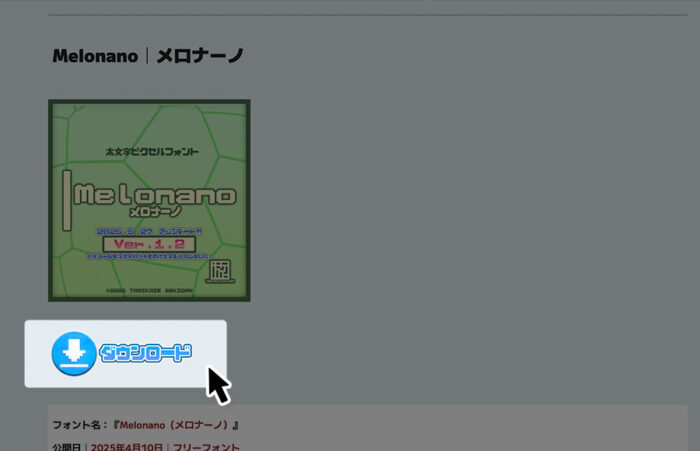
Melonano(メロナーノ)フォントは、コミカルで可愛らしい極太なピクセルフォントです。
ブロックのような太さやリズムが特徴的で、文字ごとに工夫されたシルエットが読みやすさを損なわず、レトロゲームのような懐かしさと実用性がバランス良いピクセルフォントです。
極太なウェイトのため、タイトルロゴや見出しなさまざまな場面で活用できます。
収録文字は、漢字(小学生6年生で習う漢字相当+α)・ひらがな・カタカナ・アルファベット・数字・記号が収録されています。